Как проверить похожие буквы в компактном кириллическом шрифте
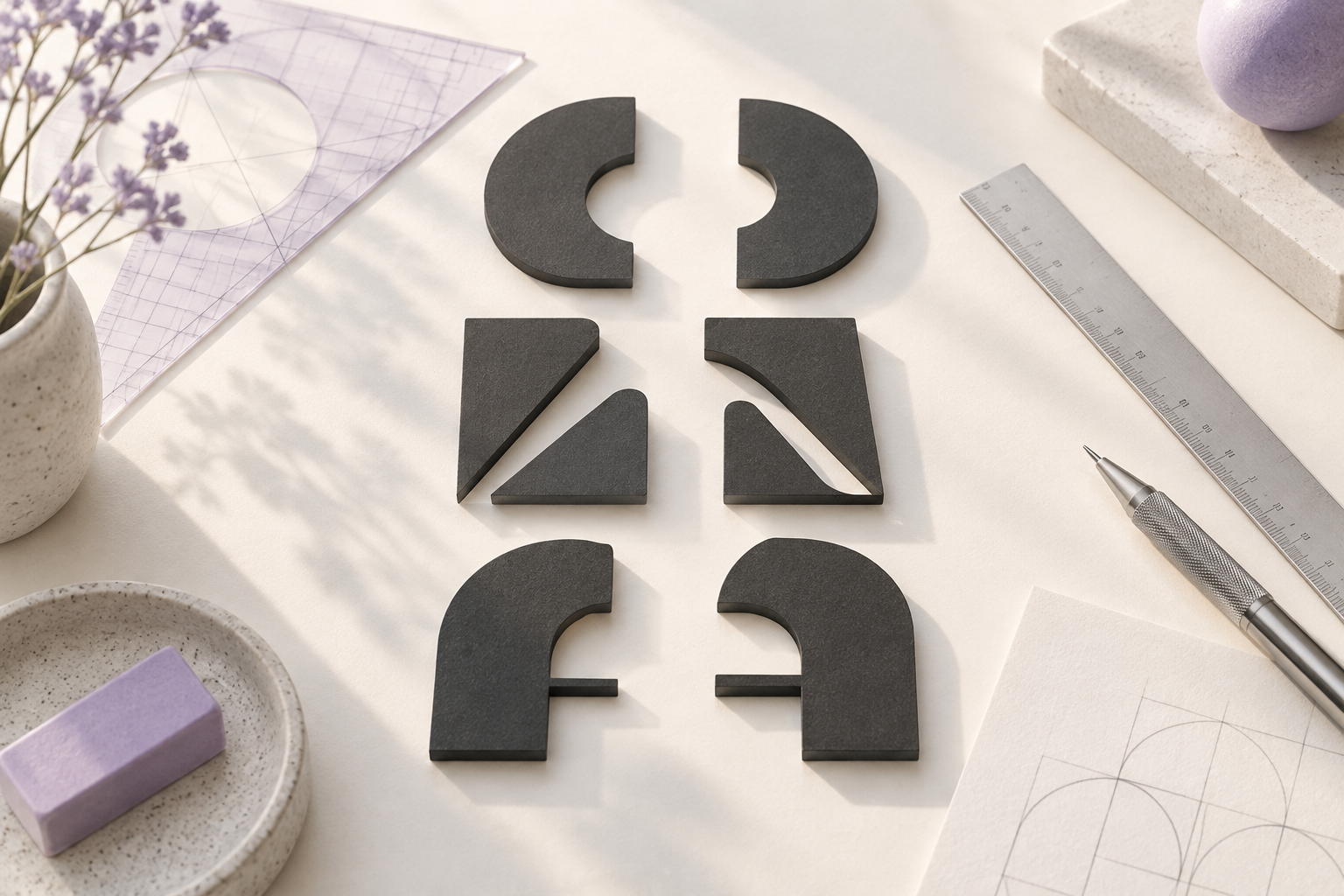
В компактном кириллическом дисплейном шрифте похожие строчные знаки нужно различать прежде всего по силуэту и внутренним просветам, а затем проверять в словах при реальном размере. Пары «а/о», «е/с» и «и/п» особенно чувствительны к тесной ширине: достаточно закрыть один просвет или упростить один штрих, и знак начинает читаться как соседний. Ниже — способ спроектировать эти различия и проверить их короткими визуальными тестами до того, как стиль будет распространён на весь набор.
Почему компактная ширина усиливает сходство
Узкий знак экономит место, но вместе с шириной часто уменьшается пространство для различий. В «а» и «о» может совпасть общий округлый контур; в «е» и «с» — открытая дуга; в «и» и «п» — две вертикали и верхняя перемычка. Если к этому добавляются жирный штрих, малый кегль или плотное соседство букв, глаз сначала считывает общий прямоугольный силуэт и только потом замечает детали. В дисплейном начертании характер можно сделать выразительным, однако стилизация должна сохранять быстрые опознавательные признаки. Поэтому оценивать нужно не только отдельную красивую букву на большом увеличении, а весь путь от контура до слова.
Полезно разделить задачу на три уровня. Первый — морфология: у каждого знака должен быть собственный узнаваемый скелет. Второй — оптическая коррекция: геометрически равные части не всегда выглядят равными, поэтому дуги, стыки и просветы приходится настраивать на глаз. Третий — контекст: соседние буквы, интервалы и словесный рисунок могут либо подчеркнуть различие, либо спрятать его. Удачное решение проходит все три уровня. Если пара различима только в увеличенном образце, но путается в заголовке, конструкция пока не готова.
Начните с признака, который нельзя потерять
Перед рисованием выпишите для каждого знака одну или две опорные особенности. Это не полный список анатомических терминов, а проектное решение: что должно остаться видимым даже при уменьшении. Для «а» это может быть узнаваемый способ соединения чаши со стойкой; для «о» — замкнутая цельная форма. Для «е» важен внутренний горизонтальный штрих и открытый вправо контур, а для «с» — ясное раскрытие дуги. В паре «и/п» сравните диагональный соединительный штрих с верхней перекладиной и боковыми стойками. Запишите признаки до полировки: так проще заметить, когда декоративный приём случайно стёр различие.
Сначала задайте общий каркас: ширину знака, высоту строчных, толщину вертикалей, характер окончания штрихов и степень сжатия. Общие параметры связывают буквы в одну гарнитуру; отличительные признаки должны пережить эту унификацию. Не обязательно делать контраст огромным. Лучше оставить общий ритм, но усилить те места, по которым читатель мгновенно узнаёт букву: открытость, соединение, направление штриха или форму внутреннего пространства. Проверьте, что изменение не делает одну букву чужой остальному алфавиту.
Пара «а/о»: сравните скелет и внутреннее пространство
Начните с двух знаков рядом, в одинаковом кегле и начертании. Смотрите сначала на внешний силуэт, затем на контрформу — пространство внутри контура. Если «а» построена на чаше с отдельной стойкой, проследите, чтобы место их встречи оставалось читаемым и не превращалось в случайную перемычку. Если выбрана одноэтажная форма, не делайте её просто «о» с приставленной ножкой: положение и направление этой части должны явно сообщать конструкцию «а». У «о» сохраняйте непрерывность замкнутого овала. В тесной ширине не закрывайте внутренний просвет чрезмерно толстой линией или оптическим сжатием.
Проведите тест на периферийное зрение: уменьшите обе буквы до рабочего размера и слегка отведите взгляд. Не пытайтесь читать детали, спросите себя, какой силуэт распознаётся первым. Затем поменяйте порядок пары и вставьте знаки в короткие фрагменты: «мама — мода», «дом — дым», «лампа — лома». Эти слова не заменяют полноценную вычитку; они помогают увидеть, как овал и характер «а» ведут себя среди повторяющихся вертикалей и округлых форм. Если без увеличения приходится вспоминать, какая буква какая, усильте конструктивную подсказку, а не добавляйте случайный декоративный хвост.
Пара «е/с»: проверьте открытие дуги
У «с» важно сохранить открытость, а у «е» — не потерять внутренний горизонтальный штрих и направленную структуру. В компактном дисплейном рисунке сжатая «с» может стать похожа на «о» с узкой щелью, а «е» — на «с», если перекладина слишком короткая или тонкая. Сравните не только ширину раскрытия, но и положение терминалов: их форма, угол среза и направление должны быть согласованы с остальной гарнитурой, однако оставлять понятную открытую сторону. В жирном начертании убедитесь, что отверстие не зарастает после утолщения штриха.
Подготовьте два образца: контурный и залитый. Контур показывает устройство дуги и перекладины, заливка — реальные просветы и оптический вес. Просмотрите пару на белом и нейтрально-сером фоне; слабый контраст фона не должен быть единственным способом найти разницу. Наберите «сено — сено» здесь намеренно повторяется только для оценки рисунка, а затем используйте разные слова: «сетка», «север», «лес», «цена». Отдельно проверьте заглавный набор, если он входит в задачу, но не переносите автоматически правила прописных букв на строчные. Исправляйте размер отверстия или длину перекладины небольшими шагами и сравнивайте версии рядом.
Пара «и/п»: различите соединение и перекладину
Эти знаки могут стать особенно похожими в тяжёлом узком начертании: оба образуют почти прямоугольный блок с двумя вертикальными сторонами. У «и» ключевое различие — диагональ, связывающая стойки; у «п» — верхняя горизонтальная перекладина и боковые вертикали. Не позволяйте диагонали стать настолько крутой или широкой, чтобы она выглядела как ещё одна стойка, и следите, чтобы перекладина «п» не создавала впечатление диагонального соединения. Проверьте места стыков: в жирном варианте там часто скапливается тёмное пятно, а в мелком — диагональ теряется.
Наберите парные последовательности «ипип», «пипи», «ими», «пили» и несколько коротких слов, в которых эти буквы стоят рядом с округлыми и узкими знаками. Смотрите на чередование светлых промежутков: если диагональ пропадает в общей текстуре, измените её наклон или точку соединения, а не только увеличивайте толщину. Проверьте также расстояние между буквами. Слишком тесная пара может слить диагональ одной буквы с вертикалью соседней; слишком широкий пробел разорвёт ритм слова. Цель теста — не добиться математически одинаковых расстояний, а сохранить ясный рисунок без пятен и случайных мостиков.
Соберите компактный набор визуальных тестов
Для ранней проверки не нужно верстать полноценный каталог. Достаточно одного листа с несколькими режимами, где версии букв показаны одинаково и их легко сравнить. Поместите пары изолированно, затем повторите их в слогах, словах и строке. Добавьте один контрастный пример: слово, где один из признаков почти исчезает из-за соседних штрихов. Не выбирайте только удобные слова с просторными округлыми буквами — короткий тест нужен именно для пограничных случаев.
- Сравните каждую пару бок о бок, а затем в обратном порядке: так порядок чтения меньше подсказывает ответ.
- Наберите короткие слова и псевдослова, чтобы проверить форму без привычной подсказки значения.
- Покажите контур и залитый знак, чтобы увидеть одновременно конструкцию и плотность просветов.
- Проверьте минимум крупный заголовочный размер, предполагаемый рабочий размер и уменьшенный предпросмотр.
- Распечатайте лист в масштабе применения или откройте его на типичном экране; не оценивайте только при увеличении.
- Сохраните рядом версии до и после правки, пометив одно изменение за раз: ширину, отверстие, угол или стык.
Слова для теста подбирайте по задаче будущего шрифта. Для плаката важны крупные короткие заголовки и быстрое чтение издалека; для упаковки — короткие названия, числа и тесные подписи; для заставки — выразительные пары и повторяющийся ритм. Если предполагается только кириллица, всё равно проверьте знаки препинания и цифры рядом с буквами: они меняют плотность композиции. Но этот тест не должен превращаться в аудит полного Unicode-набора — его цель конкретнее: убедиться, что три выбранные пары не сливаются в тех условиях, для которых проектируется гарнитура.
Как оценивать результат, а не вкус
При просмотре задавайте проверяемые вопросы. Можно ли назвать букву за секунду, не приближая макет? Сохраняется ли различие после печати или уменьшения? Видны ли опорные признаки при взгляде на слово целиком? Выглядят ли обе буквы частью одного шрифта? Если тест проводят несколько человек, попросите их сначала прочитать строки вслух или записать увиденные знаки без подсказки. Не объясняйте заранее, какая форма что означает: подсказка меняет восприятие. Зафиксируйте место ошибки, размер образца и вариант начертания, чтобы решение опиралось на конкретное наблюдение, а не на общее «кажется, нормально».
Правки делайте по одной. Если одновременно изменить ширину, толщину, наклон и интервал, будет трудно понять, что именно помогло. Сохраните исходную версию, скопируйте тестовый лист и меняйте сначала главный различительный признак. Затем проверьте, не возникла ли новая проблема: перекошенный ритм, слишком узкий просвет, тяжёлый стык или чуждый характер. В дисплейном шрифте можно позволить более заметное решение, чем в наборном, но эффектность не должна зависеть от того, что букву показывают отдельно и в крупном размере.
Частые ошибки при проектировании похожих знаков
- Полировать деталь на увеличенном контуре и забывать проверить реальный размер: тонкая подсказка исчезает первой.
- Разводить пару случайной шириной, хотя сходство создаёт форма стыка или внутреннего просвета.
- Увеличивать контраст до нарушения общего веса: одна буква начинает выглядеть чужой в гарнитуре.
- Проверять только осмысленные слова, где значение помогает угадать плохо различимый знак.
- Смотреть только на экран с сильным увеличением и не замечать, как печать или уменьшение закрывают отверстие.
- Менять несколько параметров одновременно и терять понимание, какая корректировка действительно помогла.
Ещё одна ошибка — считать, что одинаковая геометрическая ширина обеспечивает одинаковую читаемость. Оптический вес, площадь чёрного и размер внутреннего просвета могут отличаться даже у знаков в одинаковом прямоугольнике. Смотрите на пару при одинаковом кегле, но будьте готовы к небольшим оптическим поправкам. Также не оценивайте читаемость лишь по оценке автора: автор уже знает замысел и склонен «дочитывать» форму. Нейтральный просмотр без объяснения конструкции полезен даже на раннем этапе.
Чеклист перед фиксацией форм
- У каждой пары есть названный конструктивный признак, который различим без увеличения.
- «а» и «о» сохраняют разные скелеты и не теряют внутренний просвет.
- «е» и «с» имеют разное устройство и остаются открытыми там, где это требуется форме.
- Диагональ «и» не сливается с вертикалью, а перекладина «п» читается как отдельный элемент.
- Все пары проверены изолированно, в коротких последовательностях и в словах по назначению шрифта.
- Есть проверка на малом размере и версии до/после каждой существенной правки.
- Исправление усилило распознавание, не нарушив общую толщину штрихов, характер и ритм гарнитуры.
Какие буквы проверять в первую очередь?
Начните с пар, которые похожи именно в выбранной конструкции и размере. Для компактной кириллицы полезно проверить «а/о», «е/с» и «и/п», а затем добавить собственные проблемные пары, найденные в словах будущего применения.
Нужно ли делать похожие буквы шире друг друга?
Ширина может помочь, но сама по себе не решает проблему. Сначала проверьте скелет, стыки и контрформы; расширяйте знак только если это усиливает распознавание и сохраняет общий ритм компактной гарнитуры.
Как понять, что просвет слишком мал?
Уменьшите образец до рабочего кегля, посмотрите на залитую форму и распечатайте её в масштабе применения. Если внутреннее пространство превращается в тёмное пятно или исчезает, увеличьте отверстие либо пересмотрите толщину и соединения.
Можно ли тестировать псевдослова?
Да. Псевдослова уменьшают влияние знакомого значения и помогают заметить, что читатель действительно различает графические формы. Используйте их вместе с обычными словами, потому что реальные соседства тоже влияют на рисунок шрифта.
Достаточно ли показать тест только на экране?
Для цифрового заголовка экранная проверка обязательна, но печать выявляет закрывающиеся просветы и потерю тонких деталей. Проверяйте способ вывода, который соответствует будущему использованию гарнитуры.
Когда можно переходить к остальным буквам?
Переходите дальше, когда различия читаются в заданных размерах и словах, а корректировка не разрушает стиль. После распространения общих параметров на весь набор повторите тест: соседние знаки могут изменить плотность и восприятие пары.
В компактном дисплейном шрифте похожие буквы различают ясной конструкцией, сохранёнными просветами и проверкой в реальном контексте. Сначала зафиксируйте признаки каждой формы, затем сравните пары отдельно, в словах и при уменьшении. Создайте свой набор в Fontgenerator и используйте короткие визуальные тесты, чтобы уверенно довести кириллицу до цельного результата.